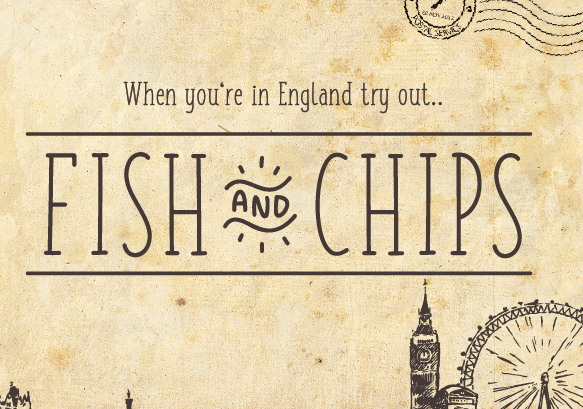
Fish&Chips Font – Download Grátis
Aqui está uma breve e envolvente descrição para a página de download da font ‘Fish&Chips’ para a categoria Typewriter Fonts: Descubra Fish&Chips – um tipo sans serif que traz vida à escrita com seu aspecto de mão escrevendo. Esta elegante fonte é livre apenas para uso pessoal, mas se você está comprando-a para uma organização com mais de dez membros, por favor entre em contato conosco primeiro através do nosso site ou e-mail: . Este projeto typewriter é perfeito para adicionar um toque único a texturas digitais. Com sua natureza natural, Fish&Chips transmite um ar autêntico e descomplicado que se adaptará facilmente à sua identidade visual. Para usuários com necessidades comerciais mais avançadas, há uma versão completa disponível junto com outros estilos dessa fonte no site do designer: www.phitradesign-fonts.com/fishandchips. Aqui você poderá explorar e escolher a melhor solução para seu projeto.